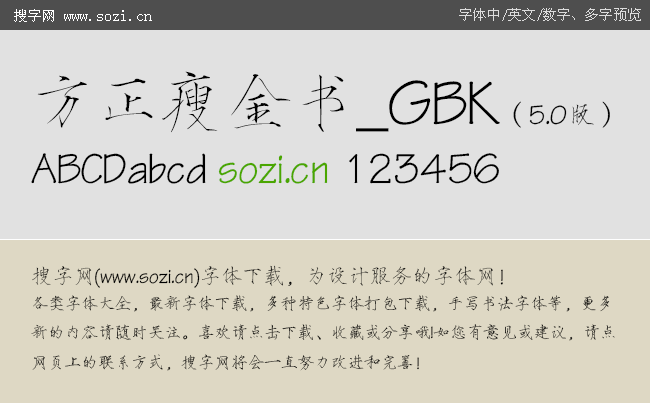
方正瘦金書-GBK
搜字網(wǎng)提供一款書法字體方正瘦金書-GBK字體下載,瘦金體為宋徽宗趙佶所創(chuàng),是書法史上的一項獨創(chuàng)。瘦金體運筆飄忽快捷,筆跡瘦勁,至瘦而不失其肉,轉(zhuǎn)折處可明顯見到藏鋒,露鋒等運轉(zhuǎn)提頓痕跡,是一種風格相當獨特的字體。適合字貼、招貼、書法畫冊設計應用。